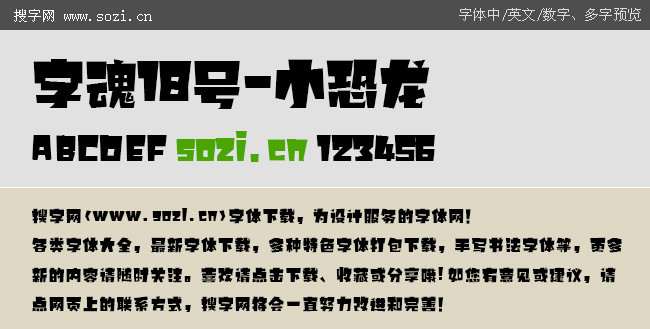
字魂18號(hào)-小恐龍
搜字網(wǎng)提供一款字魂18號(hào)-小恐龍中文字體下載,該字體是一款創(chuàng)意字體,該字體包含6763個(gè)中文、字母、 符號(hào)和數(shù)字,具有簡(jiǎn)約的風(fēng)格,可以滿足您設(shè)計(jì)上的各種需求,該字體主要用于電商等場(chǎng)景。